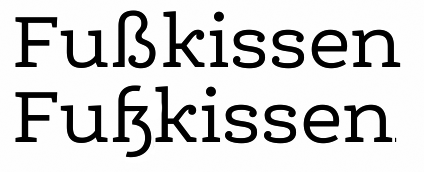
Formen des kleinen Eszett
Frage in die Runde: Wie geht es Euch mit diesen beiden Eszett-Strukturen?
(Ich weiß, dass das noch ganz grob und wabbelig ist! Es geht mir mehr ums Prinzip.)
Aus dem Ärmel geschüttelt würd ich sagen: das erste ist «üblich», das zweite wirkt auf viele «altmodisch» (oder auch dadurch schon wieder «stylisch») und erinnert an Berliner Straßenschilder. :)
Im Ernst: Heute hat mich ein Kollege darauf aufmerksam gemacht, dass das «übliche», obere Eszett als einziger Buchstabe eine «breite» Oberlänge hat, also nicht nur einen Strich nach oben, sondern tatsächlich Volumen. Während das in Worten mit anderen Oberlängen und ohne Versalien (wie «schließen» oben) nicht auffällt, wirkt es in Fonts, die «kurze» Versalien haben (so wie meiner), in bestimmten Worten schnell zu massiv (da hoch *und* breit):
Dieses Problem finde ich auf der zweiten Zeile besser gelöst (bzw. weniger akut vorhanden).
Außerdem frage ich mich, ob zu einem Versaleszett der von Andreas Stötzner portierten «Dresdner Form» ein solches Minuskel-Eszett (schon nur aufgrund der «Ecke») nicht womöglich besser passt (je nach Font natürlich):
Ich würde mich über Meinungen freuen. Vermutlich werden beide Versionen in meinem Font vorkommen, es fragt sich halt, welches der Standard werden soll. Ich gebe zu, dass ich persönlich zur zweiten Form tendiere – ich halte sie rein formal/konzeptionell für smarter, schärfer, sauberer, klarer und schöner als diese (Entschuldigung) Schnullerkurve; aber ich würd halt gerne wissen, wie «exotisch» sie heutzutage wirkt.
Frage in die Runde: Wie geht es Euch mit diesen beiden Eszett-Strukturen?
(Ich weiß, dass das noch ganz grob und wabbelig ist! Es geht mir mehr ums Prinzip.)
Aus dem Ärmel geschüttelt würd ich sagen: das erste ist «üblich», das zweite wirkt auf viele «altmodisch» (oder auch dadurch schon wieder «stylisch») und erinnert an Berliner Straßenschilder. :)
das erste ist nicht nur das übliche, es ist auch das richtige.
wir reden schliesslich nicht von einem es-zett (s+z-ligatur), sondern von einem scharfen s (ligatur aus langem und kurzem s). die zweite variante ist also das produkt eines mißverständnisses.
zu deiner eigentlichen frage:
dein kollege saß wohl etwas zu lange in der sonne.
Dieses Problem finde ich auf der zweiten Zeile besser gelöst (bzw. weniger akut vorhanden).
welches problem?
das "normale" ß ist oben breit. das ist ein faktum, aber kein problem.
oder schneidest du demnächst auch bei den blumen die köpfe ab, weil grashalme ja auch keine haben und das in einem blumenbeet ein "problem" ist?
Ich würde mich über Meinungen freuen. Vermutlich werden beide Versionen in meinem Font vorkommen, es fragt sich halt, welches der Standard werden soll. Ich gebe zu, dass ich persönlich zur zweiten Form tendiere – ich halte sie rein formal/konzeptionell für smarter, schärfer, sauberer, klarer und schöner als diese (Entschuldigung) Schnullerkurve; aber ich würd halt gerne wissen, wie «exotisch» sie heutzutage wirkt.
das versal-eszett sieht immer noch völlig bescheuert aus und hat einen sehr, sehr begrenzten anwendungsrahmen, so dass ich es nicht als orientierungsmarke für irgendwas heranziehen würde.
das minuskel-eszett in der alten form wirkt auf mich altmodisch und exzentrisch. als alternativbuchstabe für bestimmte einsatzzwecke ok, als standard stilistisch daneben – schnullerkurve hin oder her
Die zweite Version ist unbedingt die bessere. Sie hat Charme und sie ist auch die richtige, denn natürlich ist das ß eine ?-?-Ligatur. Schön wäre es natürlich, wenn man dann auch noch ein ? mit Unterlänge in der Schrift hätte, sei es als Alternativbuchstabe oder als Standard.
Das einzige, was man für das erste ß anführen könnte, ist die Sehgewohnheit, die dazu führt, daß die zweite Form als »excentrisch« wahrgenommen wird. Aber dem kann man nur entgegenwirken, wenn man mehr Eszetts in der zweiten Form unter die Leute bringt.
dein kollege saß wohl etwas zu lange in der sonne.
Du bist wohl etwas zu früh aufgestanden? Das kann nicht gutgehen, wenn man 6.42 Uhr schon am Rechner sitzt.
Ich baue ja auch meistens beide Formen ein, aber die Standard-Form ist meiner Meinung nach die erste:
- sie ist gewohnt, die zweite ist ungewohnt. (da kann man ganz langsam gegensteuern, aber ich mag dass meine Schriften funktionieren, nicht missionieren.)
- die zweite Form hat Ober- und Unterlänge (das hat sonst nur das thorn) und wirkt meist ziemlich groß. Man muss sie ziemlich schmal machen damit sie nicht heraussticht.
Schnullerform: ich kenn das, ein fürchterliches Genudel, man versucht sich an der x-Höhe zu orientieren, am s, man lässt verkümmern, ausschweifen, ... und nie "passt" es. Ich verstehe jeden amerikanischen Schriftgestalter, der kein ß hinkriegt, wer's nicht 1000x gesehen hat tut sich damit bestimmt noch viel schwerer.
Zu deinen konkreten Formen: Kriegt das ß noch einen Anstrich (einen halben f-Querbalken)? Ich bin mir da ja auch nie sicher bei Serifenschriften ...
Beide Formen in der fetten Belwe (1926)
Knuffig: Magere Glass-Antiqua (1912) – sowas könnte ich mir evtl. ganz gut vorstellen:
Immer noch zu exotisch?
Knuffig: Magere Glass-Antiqua (1912) – sowas könnte ich mir evtl. ganz gut vorstellen:
Hast du schon mal eine Form wie die »2« auf der Grafik ausprobiert?
(Also mit diesem kleinen Knick, wo die »s-Form« anfängt.)